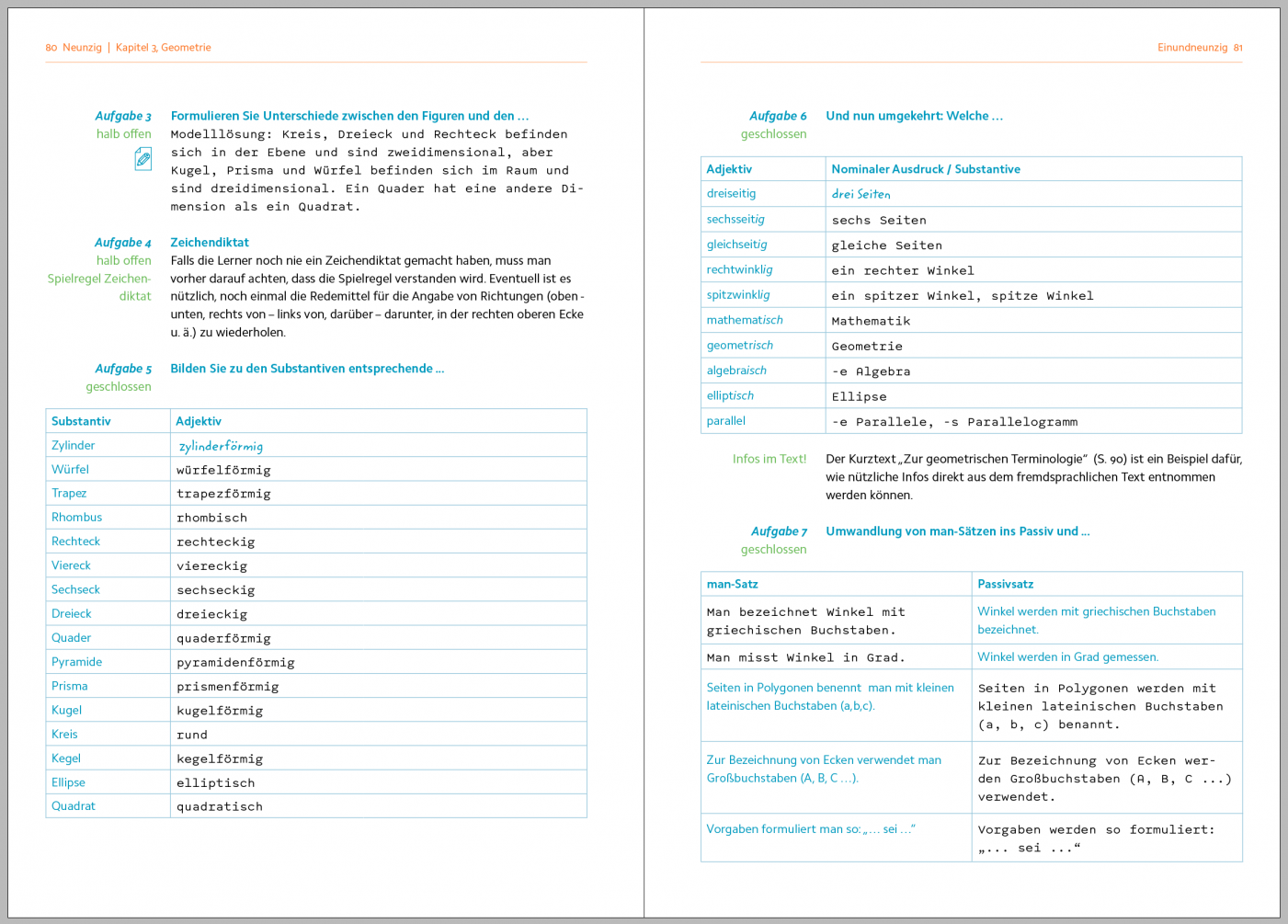
Mathematischer Formelsatz M O N O S P A C E D ?
jetzt habe ich hier munter und mit Interesse zwei gute Stunden im Forum alles durchsucht was mit wissenschaftlichem Satz und Formelsatz zu tuen hat. Aber leider nichts gefunden was mir hilft.
Für ein Lehrbuch "Deutsch für Ingenieure" wurde ich gebeten den Lösungsschlüssel zu gestalten. Da im Buch selbst für verschiedene Ebenen schon alles möglichen an Sans- und Serifschriften genutzt wurde, bleibt für die Lösungen nur noch eine Monospace damit es sich gut kenntlich und auf den ersten Blick von den anderen Inhalten abgrenzt. Nun habe ich als Möglichkeiten nur die Computer-Modern gefunden die ja leider sehr unschön ist sowie die Thesis die aber nur die Sans als Mono ausgebaut hat und das ist mir wiederum zu wenig Kontrast zum vorhandenen Text. Gibts da noch weitere Möglichkeiten die was taugen?
Meine Wahl bis jetzt wäre die Spot - Mono von Schick-Toikka. ( http://www.schick-toikka.com/projects/spot-mono )Ich dacht durch den kompletten grichischen Zeichensatz wäre ich auf einem guten Weg, leider gibt es nur diagonale Brüche und daher wäre das dann ein Fall für Formeln mit der Handbauen.
Welche Schriftarten sind schon im Einsatz?
sowie die Thesis die aber nur die Sans als Mono ausgebaut hat und das ist mir wiederum zu wenig Kontrast zum vorhandenen Text. Gibts da noch weitere Möglichkeiten die was taugen?
Verstehe ich noch nicht so richtig. Du suchst als Kontrast eine Monospace, aber eine Monosapce-Sans reicht Dir nicht?
Also das Buch ist zum Großteil mit der Comphor Pro gesetzt ca 80%. Es gibt einige Strecken die in der CaeciliaLT gesetzt sind. Und an ein paar stellen gibt es eine Beispiel Lösungen in der ZemkeHand. Dazu gibt es einige Farbige Auszeichnungen daher fällt Farbe leider auch weg.
Welche Schriftarten sind schon im Einsatz?
Verstehe ich noch nicht so richtig. Du suchst als Kontrast eine Monospace, aber eine Monosapce-Sans reicht Dir nicht?
Genau!
Der Anhang ist eine Seite als Beispiel mit der Spot als Schrift für die Lösungen. Alle anderen Schriften und das Seiten-Layout sind so gesetzt.
Edit: Sorry die Qualität beim Upload ist ja leider nix. Vielleicht besser so:
Vermutlich ist das ja schon geprüft und verworfen, aber ich frag trotzdem mal: Eine Kursive kommt stattdessen nicht in Frage?
Nein leider nicht da einige mathematische Zeichen selbst Kursiv sind.
Hoffentlich findest du eine, bei der sich dieses wahrscheinlich häufig verwendete Wort nicht ganz so sehr wie Mode111ösung liest! ;-)
Hast du schon bei Myfonts gesucht? Die für die »nicht-diagonale«¹ Darstellungsform von Brüchen zuständige Opentype-Funktion heißt ja Alternative Fractions (afrc), so dass diese Suchanfrage vielleicht interessant wäre: https://www.myfonts.com/search/ot_exact%3Aafrc/fonts/
(Da nur wenige Fonts diese Funktion unterstützen, habe ich mal nicht weiter nach Monospace, Serifen o.ä. gefiltert.)
1. Auf Englisch nut fractions oder stacked fractions. Gibt es einen deutschen Fachbegriff?
Ok, als ich eben postete, war ich etwas in Eile, sorry. Jetzt nochmal, ausführlicher – die Verwendung eines dicktengleichen Fonts wirkt für mich unharmonisch, daher meine Frage, ob eine Kursive es nicht auch tut. Wie ich jetzt verstanden habe, ist das keine Option.
Meine Frage, besser formuliert als oben, wäre eigentlich: Gibt es typografische Alternativen zur Monospaced? Ich sehe, dass das Ganze farbig gedruckt wird, wäre eine farbige Hinterlegung, oder eine bestimmte Schriftfarbe nur für Lösungen, eventuell eine Alternative?
Nicht dass ich meinte, Du hättest nicht schon überlegt, aber manchmal kann ein Anstoß zum Neu-Denken ja auch nutzen.
Ich sehe das nicht als Ausschlusskriterium. Mathematische Formeln sollten selbst für Sprachlerner deutlich vom eigentlichen Text unterscheidbar sein. In wissenschaftlichen Arbeiten ist es relativ normal, dass kursive Symbole mal in aufrechten, mal in kursiven Text eingebettet sind.
Insbesondere tauchen gerade in Deinem Beispiel ja auch aufrechte mathematische Symbole auf und mit derselben Argumentation dürftest Du dann auch keine aufrechten Schriften irgendwo nutzen.
@Þorsten: Danke für die genau Bezeichnung der alternativen Brüche. Die Suche hat leider auch das gewünschte nicht ans Licht gebracht. Dann muss ich wohl doch nochmal in eine andere Richtung schauen. Das mit der Modelllösung finde ich nicht so schlimm.
@BerndH: Danke auch für eure Anregungen. Ich werde da jetzt nochmal in mich gehen. Vielleicht gibt es ja noch eine andere Form der Abgrenzung zu dem Bestehenden die ich nicht bedacht habe. Farbe ist, wie ich finde recht schwer, da die meisten Farben aus dem Farbkreis schon im Buch mit Funktionen besetzt sind aber man kann nicht oft genug das ganze nochmal von vorne denken.
@ Wrzlprmft: Da ist was dran. Es geht mir aber primär um eine klare Unterscheidung von Lösung und Aufgabe. Mal sehen was das noch gibt.